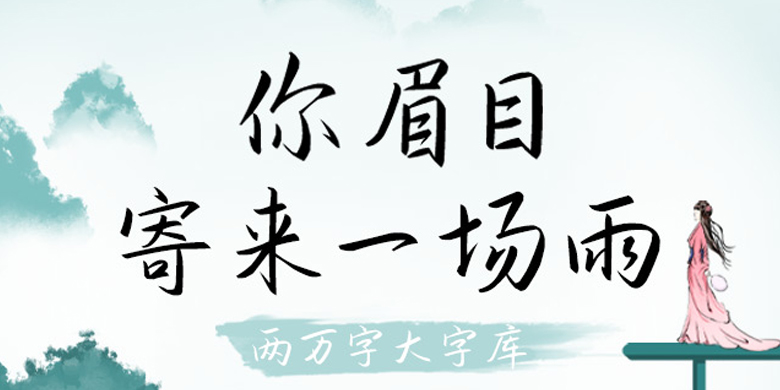
方正手迹-你眉目寄来一场雨
方正手迹-你眉目寄来一场雨,这款字体结构工整、笔画清晰,兼顾美观与易读性,适用于标题、正文、海报、包装、LOGO 等多种场景。字形优雅稳定,风格百搭耐看,适配日常排版与创意设计,让文字呈现更舒适、更具质感。方正手迹-你眉目寄来一场雨一笔一画,皆是细节,以均衡的比例、流畅的线条打造舒适视觉体验,字形端正大气,风格简约现代。无论是商业设计、品牌宣传还是日常排版,都能轻松驾驭,让文字更有格调与力量。方正手迹-你眉目寄来一场雨字体下载。
该款字体粗细过度较大,风格独特,艺术个性鲜明,转角圆润,稍带连笔,给平稳的结构带来了一丝律动,雅俗共赏。适用于文艺类的书刊、品牌广告和产品包装设计,以及社交网络的个性化用字。